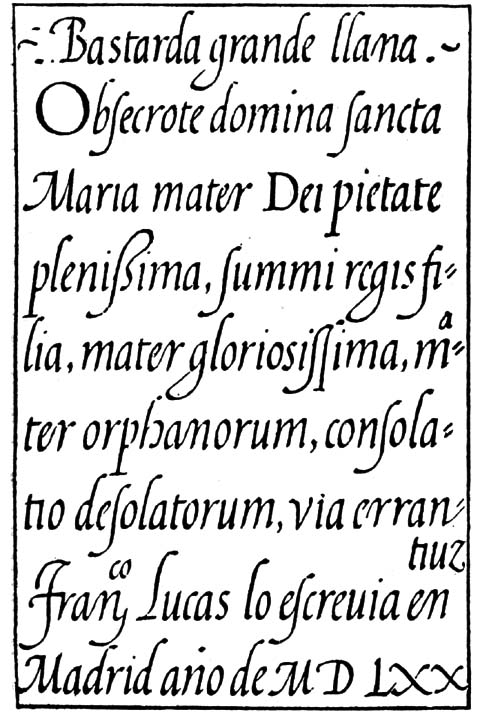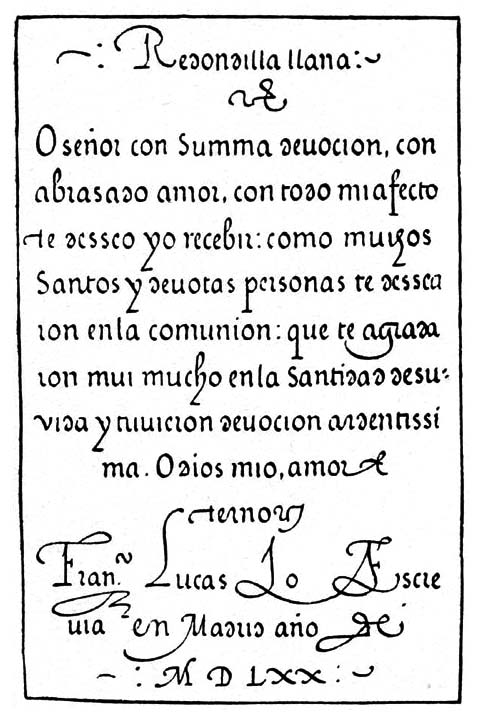
Francisco Lucas(1580, Arte de Escrivir) Mestre-calígrafo espanhol.A sua obra-mestra é Arte de escrevir. Madrid, 1580. «Francisco Lucas fue un excelente pendolista. Escribió liberalmente letra grifa, redondilla y antigua, y su Bastarda fue de tal belleza, que influyó extraordinariamente en la forma de la letra española durante dos siglos. Con razón, pues, considera Torío a Francisco Lucas como calígrafo eminente. » «Además, modificó de tal manera los trazos duros de la letra de Madariaga, que puede ser considerado como el reformador de la letra española, cuyo carácter fijó de admirable manera, dándole una rotundidad que aún conserva.» (Citação de: Arte de la Escritura y de la Caligrafía (Teoría y práctica) Rufino Blanco y Sánchez)